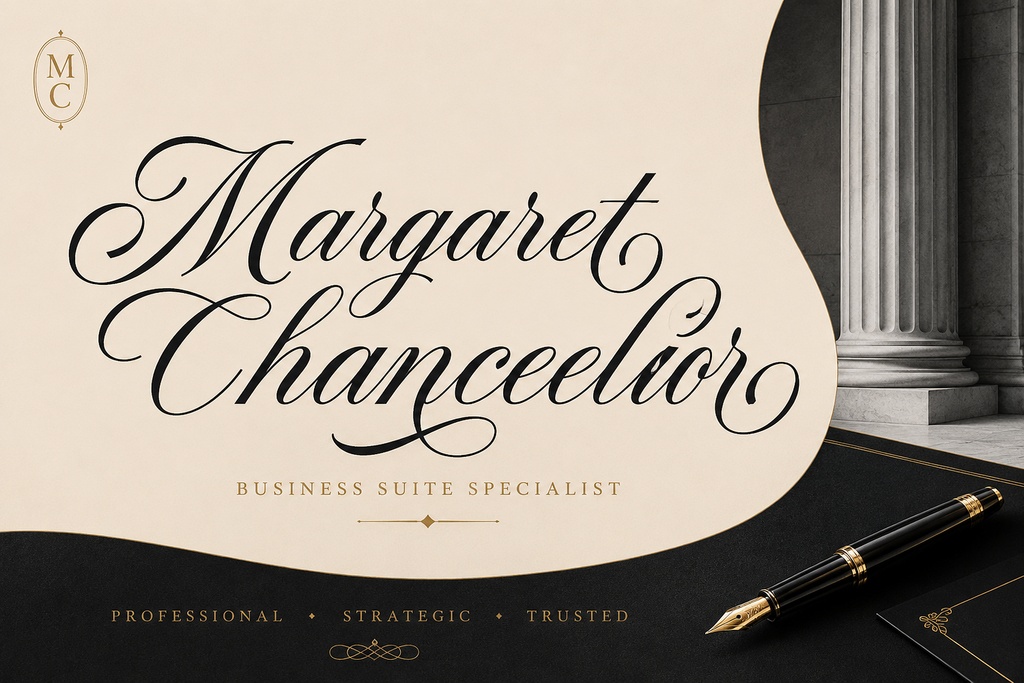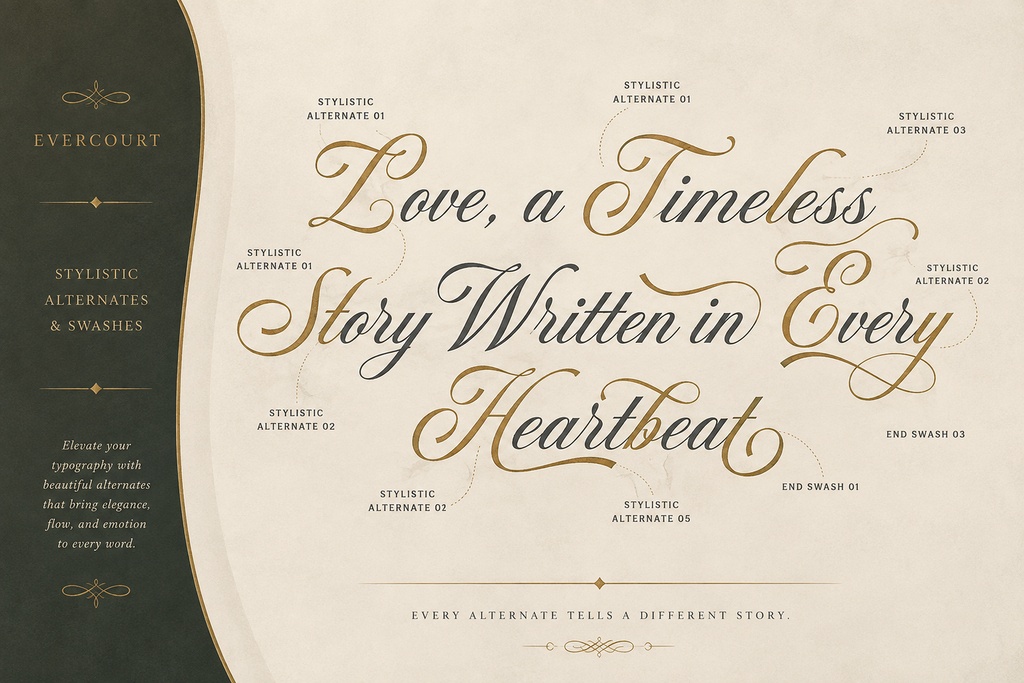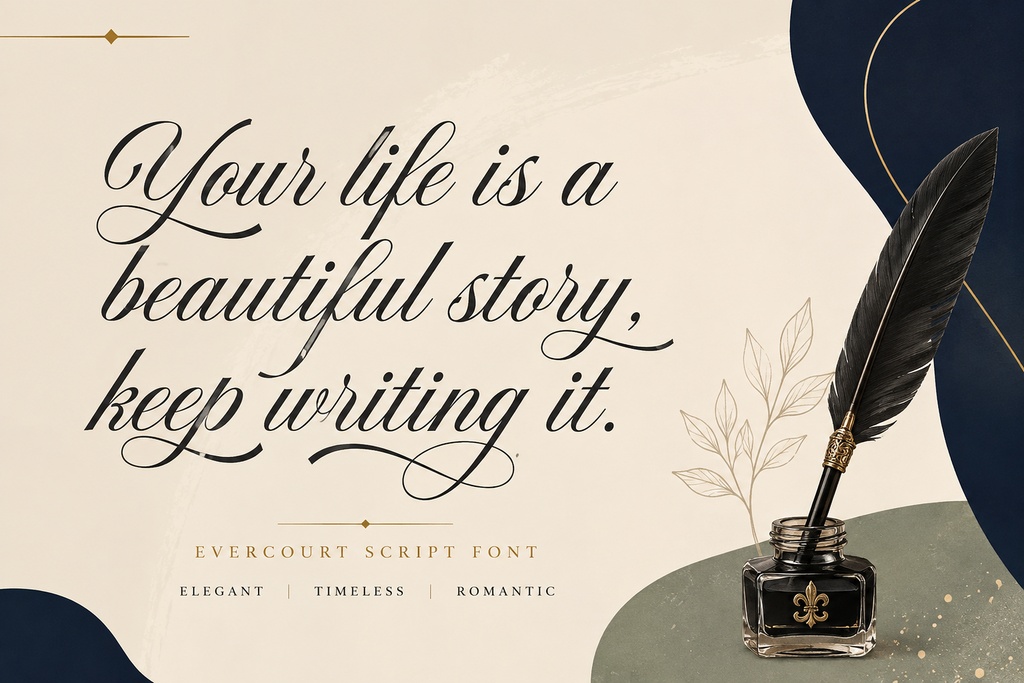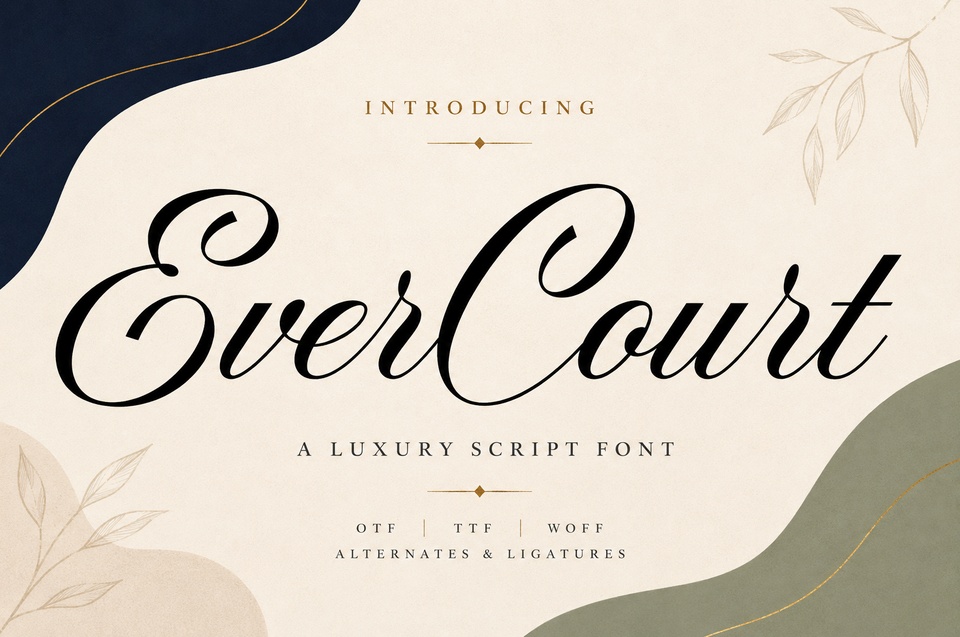
Evercourt — スワッシュ付きのロマンチックなスクリプトフォント
Evercourtは、言葉に感情が宿る瞬間のために作られたロマンチックなスクリプト書体です。ウェディング招待状、ステーショナリーセット、ラブレター、そしてメッセージそのものが美しく見えるべきあらゆる記念の場面に最適です。流れるような大文字とつながりのある小文字は、手作業で仕上げたようなリズム感を持ち、装飾的なエンドスワッシュやスタイル代替文字によって、あらゆるレイアウトをオーダーメイドのように演出できます。 この書体は単一のRegularスタイルで提供されます。複雑なウェイト選択に迷う必要はなく、フルページの招待状から小さなモノグラムまで、ひとつの統一された雰囲気で使用できます。ファイルには、丁寧に作り込まれた363種類のグリフが収録されています。完全なBasic Latinの大文字・小文字、数字、句読点、そしてオリジナルデザインに含まれる装飾的な代替グリフを備えています。OpenType機能にはGSUBおよびGPOSテーブル、6種類のスタイルセット(ss01〜ss06)、さらにエンドスワッシュが含まれており、デザインアプリのGlyphsパネルから直接、代替文字や装飾的なフローリッシュを切り替えることができます。 主な特徴: 装飾的なスワッシュ — エンドスワッシュが招待状、モノグラム、エディトリアルデザインに手書き感のある優雅なアクセントを加えます。 スタイル代替文字(ss01〜ss06) — 文字を描き直すことなく、控えめな雰囲気から華やかな印象まで自由に変更できます。 つながりのある小文字 — 見出し、引用文、サイン風テキストに自然な筆記体の流れを提供します。 363グリフ — 完全なBasic Latin、数字、句読点、装飾的な代替文字を1つのファイルに収録。 OTF、TTF、WOFF、WOFF2対応 — デスクトップ、ウェブ、モバイル環境を1つのパッケージでカバー。 特に適した用途: ウェディング招待状、セーブ・ザ・デートカード、式典プログラム、お礼状やステーショナリー、フローリストやイベントプランナー向けのブランディング、商品パッケージ、グリーティングカード、バレンタインや記念日のキャンペーン、エディトリアル見出し、そしてロマンチックで人間味のある雰囲気が必要なロゴデザインなどに最適です。 互換性: Adobe CC(Illustrator、InDesign、Photoshop)、Figma、Canva、Procreate、Affinity、Cricut Design Space、Silhouette Studioで使用できます。また、付属のWOFF/WOFF2ウェブフォントを利用することで、最新のウェブ環境にも対応しています。 ライセンス: この商品はCubebrush Commercial Licenseのもとで商用利用が許可されています。クライアント向けの制作物や販売商品に使用でき、クレジット表記は必要ありません。このフォント自体は手作業で制作された書体であり(AI生成グリフではありません)、安心して商用プロジェクトに利用できます。 次の招待状やブランドプロジェクトに、手書きのような温かみのある個性を与えましょう。Evercourtをカートに追加して、デザインを始めてください。